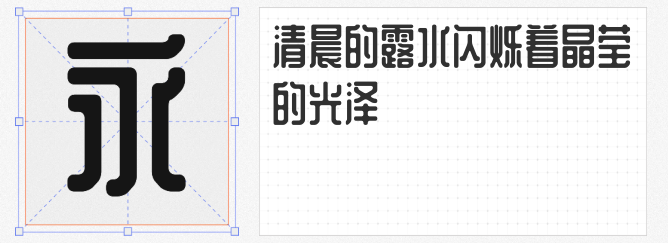
在海报设计中,标题字体是视觉传达的核心元素,选择一款风格鲜明、辨识度高的字体能瞬间提升作品吸引力。以下四款免费商用字体,涵盖像素风、几何对比、力量感与创意设计,助你轻松打造令人过目难忘的标题效果。
作为ChuLyu字体的升级替代品,粗柳坊新16x Bold以像素风格独树一帜。其16x16的像素网格设计保留了复古游戏与数字时代的粗粝质感,适合科技、潮流或怀旧主题海报。字体笔画粗壮均匀,边缘锐利,即使在小尺寸下也能保持清晰,尤其适合作为主标题或强调性文字,瞬间营造出强烈的视觉冲击力。
仓耳非白 W04以“黑与白”的哲学为灵感。其方正结构与直角转折赋予字体现代工业感,而圆形点笔与细线装饰则柔化了整体线条,形成刚柔并济的独特风格。适合极简、时尚或品牌类海报,通过强烈的视觉对比传递高级感。
仓耳与墨 W04将篆刻的“刀意”融入现代字体设计,笔画模拟刀刻痕迹,转折处以圆角中和锐利感,形成“内方外圆”的张力。配套英文与标点延续统一风格,适合文化、艺术或运动类海报,传递厚重与前卫并存的视觉语言。
基于站酷庆科黄油体优化升级的WD-XL滑油字 SC,通过补全繁体中文与标点符号,成为大中华区设计的实用之选。字体笔画圆润如黄油般顺滑,部分结构优化后更显协调,适合美食、生活或亲子类海报,营造轻松愉悦的氛围。
这四款字体均支持免费商用,无论是追求复古像素、几何对比、刀刻力量还是圆润创意,都能为海报标题注入独特灵魂。设计师可根据主题需求灵活搭配,让作品在信息洪流中脱颖而出!